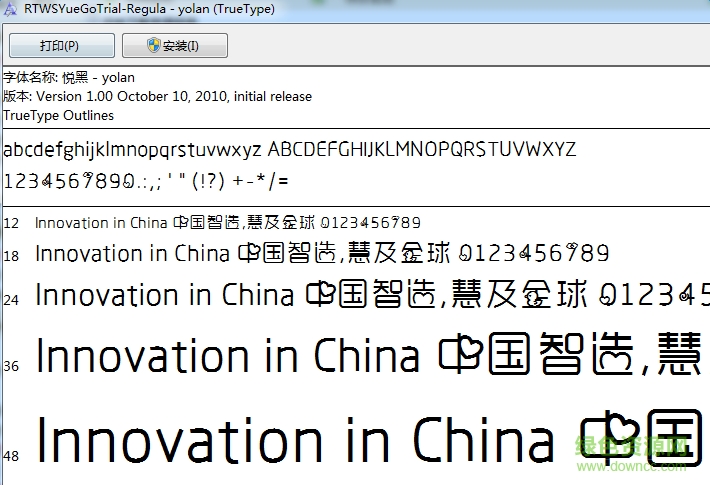
蝸牛的愛(ài)情個(gè)性字體
蝸牛的愛(ài)情字體是一款超好用的中文個(gè)性字體,一個(gè)個(gè)字體都仿若蝸牛在里面爬行,給字體賦予了新的生命力,具有更生動(dòng)的形象,對(duì)于平面設(shè)計(jì)的朋友來(lái)說(shuō)是一款必不可少的字體,喜歡的用戶就趕快來(lái)綠色資源網(wǎng)免費(fèi)下載收藏吧!
蝸牛的愛(ài)情字體是一款極具個(gè)性的字體,該字體十分飄逸,彰顯了自己的個(gè)性,有喜歡的朋友可以來(lái)綠色資源網(wǎng)下載使用!